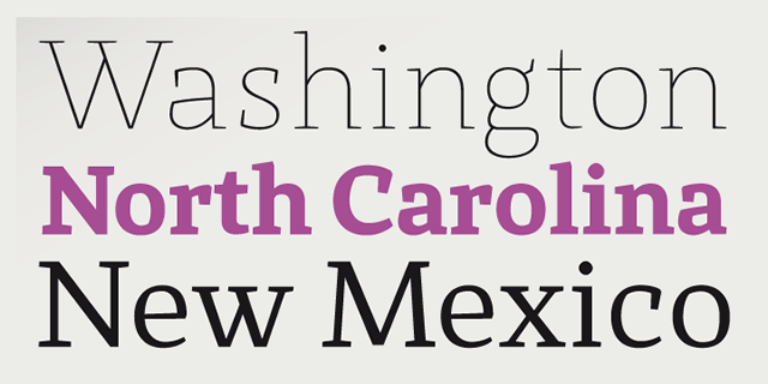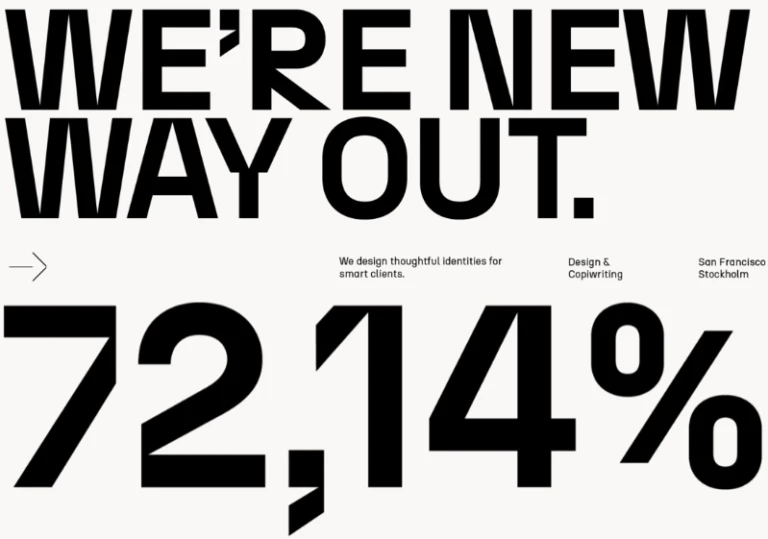
49 Gratis fonts voor professionals: de ultieme lijst
Laatst bijgewerkt: 20-10-2025 ★ Wie houdt er niet van gratis fonts? De kracht van typografie is enorm. De grote wereldmerken hebben allemaal hun eigen custom corporate font, want lettertypes bepalen voor een groot deel het succes van een merk. Naast custom fonts zijn er miljoenen freeware lettertypes die we onder de loep genomen hebben. Design agency Stoere Binken Design heeft een uitgebreide verzameling van gratis fonts die jij als professionals vandaag nog wilt gebruiken. Wil jij gratis mooie lettertypes proberen? Dan is dit blog voor jou!
Zeg nou zelf: hoe moeilijk is het om goede gratis fonts te vinden die je ook voor je commerciële projecten kunt gebruiken?
Precies daarom hebben wij deze uitgebreide – en constant groeiende – collectie van free fonts samengesteld. Deze mooiste lettertypes families kun jij voor logo’s, huisstijlen, magazine titels, hoogwaardige verpakkingen of elke andere creatieve hersenspinsels gebruiken. Soms zelfs als web font voor internet toepassingen. Dit zijn onze beste tips als de jongens van de branding.
1 – N27 (Regular & Italic)
N27 is een moderne avant-grotesk van atipo. De afgesneden lettertekens en kantige hoeken maken het font uitermate geschikt voor kunst & cultuur, design en architectuur. De N27 werkt geweldig in het groot, want dan komen de details goed tot zijn recht.
1 – Meqanor
Meqanor is als lettertype een klasse apart. Het behoort tot de onderscheidende categorie van display serifs, ontworpen om een ​​statement te maken en de aandacht te trekken. Gemaakt met precisie en creativiteit, onderscheidt Meqanor zich als een uniek en onderscheidend lettertype dat een vleugje verfijning aan elk ontwerp toevoegt.
1 – Scalone
Scalone is een psychedelicsh display font, een levendig en betoverend lettertype dat moeiteloos de retro charme van psychedelische kunst combineert met een moderne twist. Dit lettertype is een mix van creativiteit, individualiteit en de gedurfde geest van het onconventionele.
1 – Brenat
Brenat is een modern, veelzijdig én gelaagd (!) sans serif lettertype dat moeiteloos verfijning combineert met een vleugje eigentijdse flair. Brenat is met precisie en aandacht voor detail gemaakt en is ontworpen om jouw creatieve projecten een lichte 80s touch te geven. De strakke lijnen, evenwichtige verhoudingen en unieke laag-opties maken het font heel breed toepasbaar.
1 – Magilio
Een prachtig en zacht lettertype in een eigentijdse stijl die je ontwerp projecten er modern, elegant en luxueus uit laten zien. Gemaakt met veel alternatieve tekens om je ontwerp diverser vorm te geven, te variëren met verschillende lettertekens en ligaturen.
Je kunt Magilio toepassen in een breed palet aan ontwerpen zoals social media berichten, logo’s, merchandise, verpakkingen, boekomslagen, posters, video-inhoudsminiaturen, citaten, landingspagina’s, huwelijksuitnodigingen en nog veel meer.
1 – Zighead
De stijl van het Zighead lettertype is momenteel super hot. Modern met een touch van Art Nouveau. Het heeft sterke en unieke schreefletters die vloeien als een rivier van inkt. Een combinatie van scherpe punten en vloeiende rondingen, is interessant en toch speels, en biedt die extra flair waarnaar je op zoek bent. Dit decoratieve lettertype zal zeker opvallen, met zijn zeer gestileerde, flamboyante vormen die perfect zijn voor het creëren van woordmerken en typografische posters.
1 – Brutal Type Extra Light
Brutal Type is een schreefloos lettertype met een uitgesproken mannelijk karakter. Het is gebaseerd op de vormen van het DIN-lettertype, hoe radicaal ook heroverwogen. Ondanks de ogenschijnlijke eenvoud en vanzelfsprekendheid van vormen, is het ontwerp van Brutal Type origineel en fris. Dit lettertype is universeel en voor iedereen vertrouwd, emotioneel en pakkend tegelijk.
Brutal Type is ontworpen door Gayaneh Bagdasaryan, Dmitry Rastvortsev en uitgegeven bij Brownfox.
1 – Grandis
Grandis (“chainlink”) was aanvankelijk bedoeld voor de gebruikersinterface van een first person shooter game. Het lettertype moest leesbaar zijn met behoud van het sci-fi gevoel. Dit betekende een grote x-hoogte, steile diagonalen en vierkante kommen om de hoeveelheid witruimte tussen letters te verminderen. Tabel cijfers (tabular figures) vergemakkelijken het ontwerp van de gebruikersinterface waar timers of tabellen bij betrokken waren.
Wat het lettertype onderscheidt van soortgelijke grotesken, zijn de klassieke verhoudingen van de letters met brede kommen en smalle rechthoeken. Het resultaat is een leesbaar, veelzijdig werkpaard met een interessant dynamisch ritme.
Grandis is ontworpen door Eimantas Paškonis en het heeft maar liefst 36 stijlen. 6 daarvan zijn gratis! Het ondersteunt ook meertalig Latijn en Cyrillisch, inclusief Bulgaarse en Servische alternatieven.
De gratis fonts van René Verkaart zijn een echte aanrader! Maar neem zeker een kijkje bij Characters Font Foundry voor de custom fonts die René voor internationale bedrijven ontwikkeld heeft. Je kunt een groot deel van zijn lettertypes proberen. Gratis!